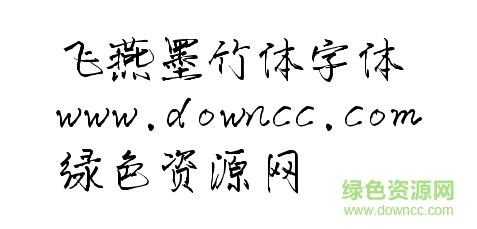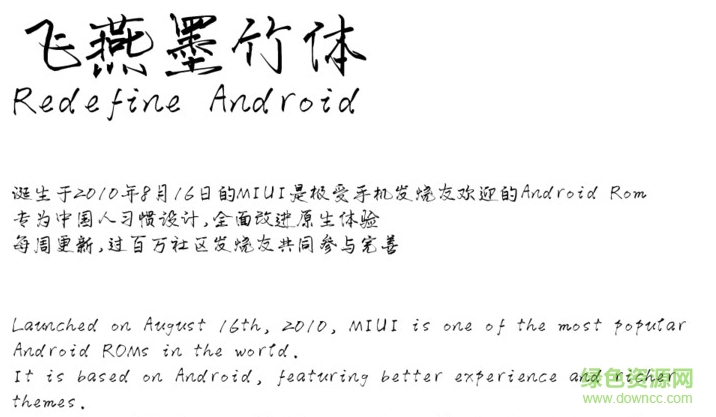
飛燕墨竹體
飛燕墨竹體是一款國風(fēng)字體,潑墨畫的手寫體風(fēng)格,給你舒適大方的視覺好感,兼具鋼筆字體毛筆字體之風(fēng),讓文字剛?cè)岵?jì),美感十足,喜歡就來綠色資源網(wǎng)下載吧!
飛燕墨竹體字體簡(jiǎn)介
這是一款行楷鋼筆手寫風(fēng)格的字體,銀鉤鐵畫的行筆風(fēng)格,有如飛燕般奮筆疾書的動(dòng)感,又獨(dú)具凌厲粗獷的字形,如墨竹的鋒芒,銳氣十足。
墨竹背景
墨竹是竹子的一種,墨畫的竹子,相傳始于唐代吳道子。北宋的文同、清代的鄭板橋都是畫墨竹的名家。北宋畫家文同作品。圖中竹竿像弓,彈性十足、竹葉如劍、蓄勢(shì)待發(fā),展現(xiàn)了強(qiáng)勁的筆力。